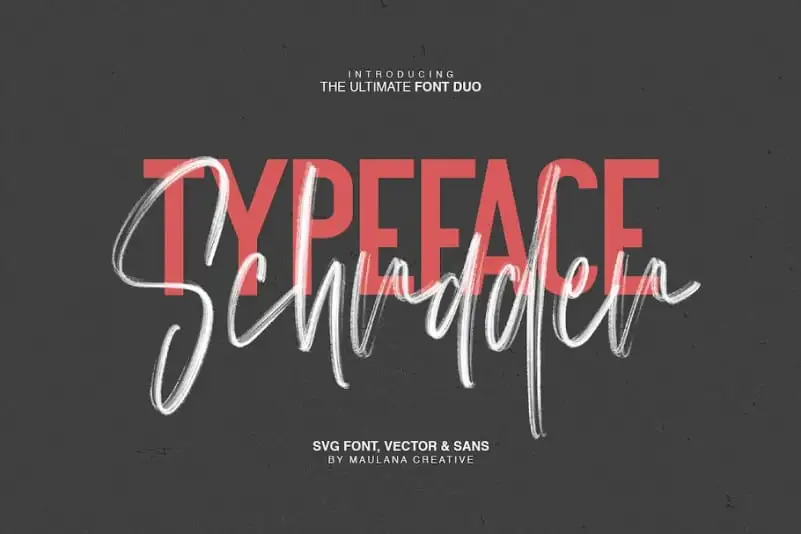
Schrader SVG Brush Font – Download Grátis
A Schrader Font é uma deliciosa dupla de fóruns SVG, composta por um SVG Brush e um tipo sans-serif, perfeita para design pessoal, logotipos e trabalhos incríveis. Desenvolvida e compartilhada pelo Maulana Creative, a fonte oferece uma sensação genuína de canetadas artesanais em seus designs. “Schrader” é ideal para assinaturas, materiais de correspondência, logotipos, citações tipográficas, capas de revistas ou livros, cabeçalhos de websites, roupas, marcação e embalagens. Com sua textura fluida e estilo único, a Schrader é perfeita para adicionar um toque autêntico ao seu design. Seja você um designer profissional ou iniciante, essa fonte irá certamente encantar com sua beleza e versatilidade. Descubra como transformar seus trabalhos em uma verdadeira obra de arte com a Schrader Font.